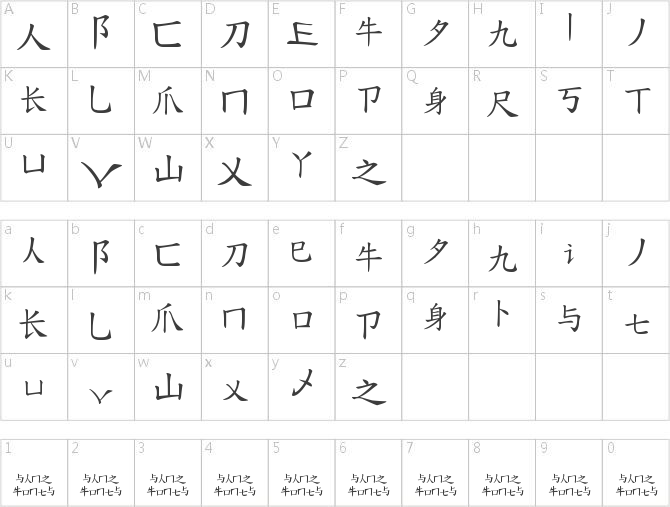
字體名稱: message
messagefromtheeast
messagefromtheeast介紹
messagefromtheeast字體字庫是一款讓人賞心悅目、百看不厭的英文字體,適合各類廣告和產品包裝設計應用,字體大小0.02MB,格式為ttf字體,上傳用戶是gagilang,作者/版權方為未知